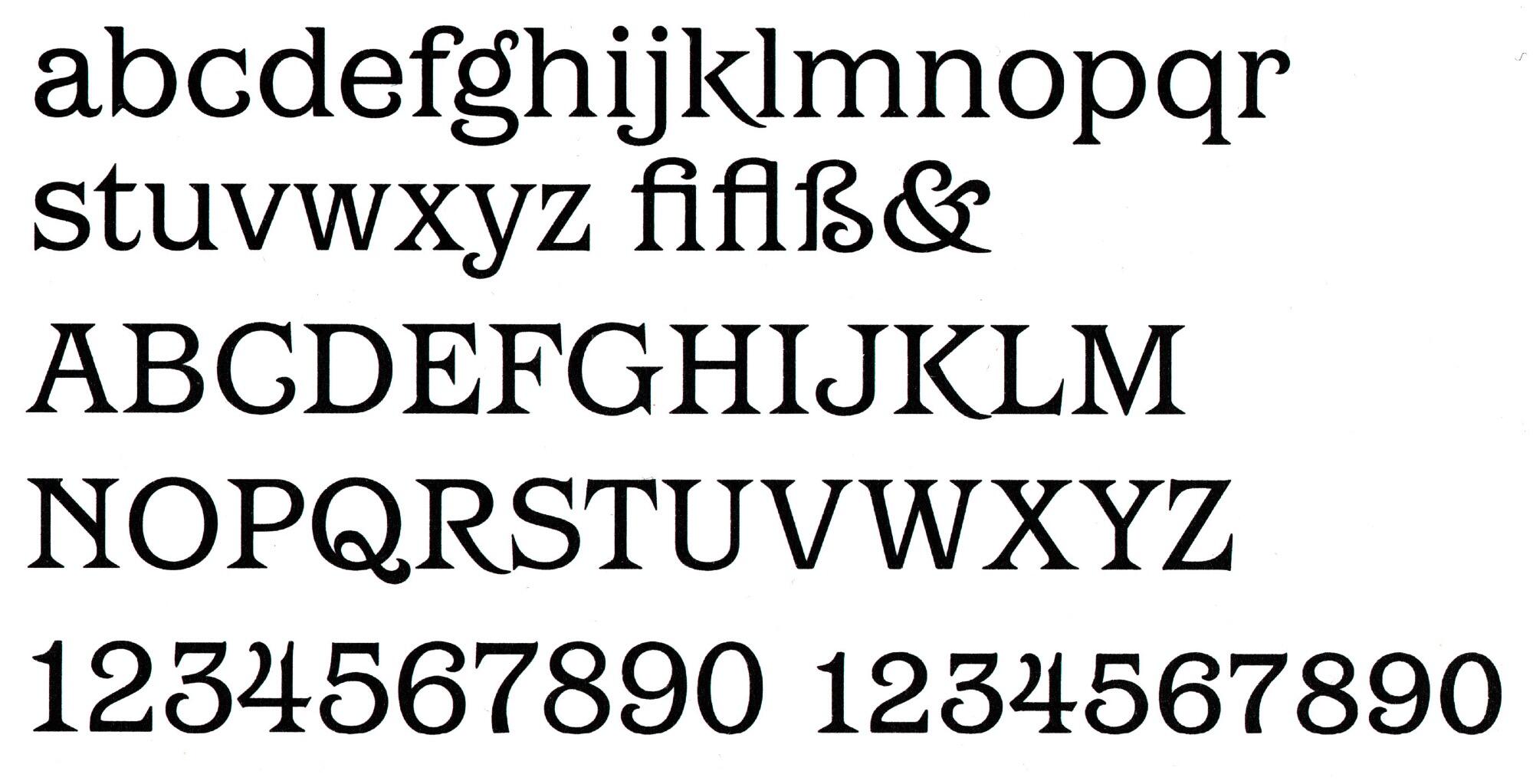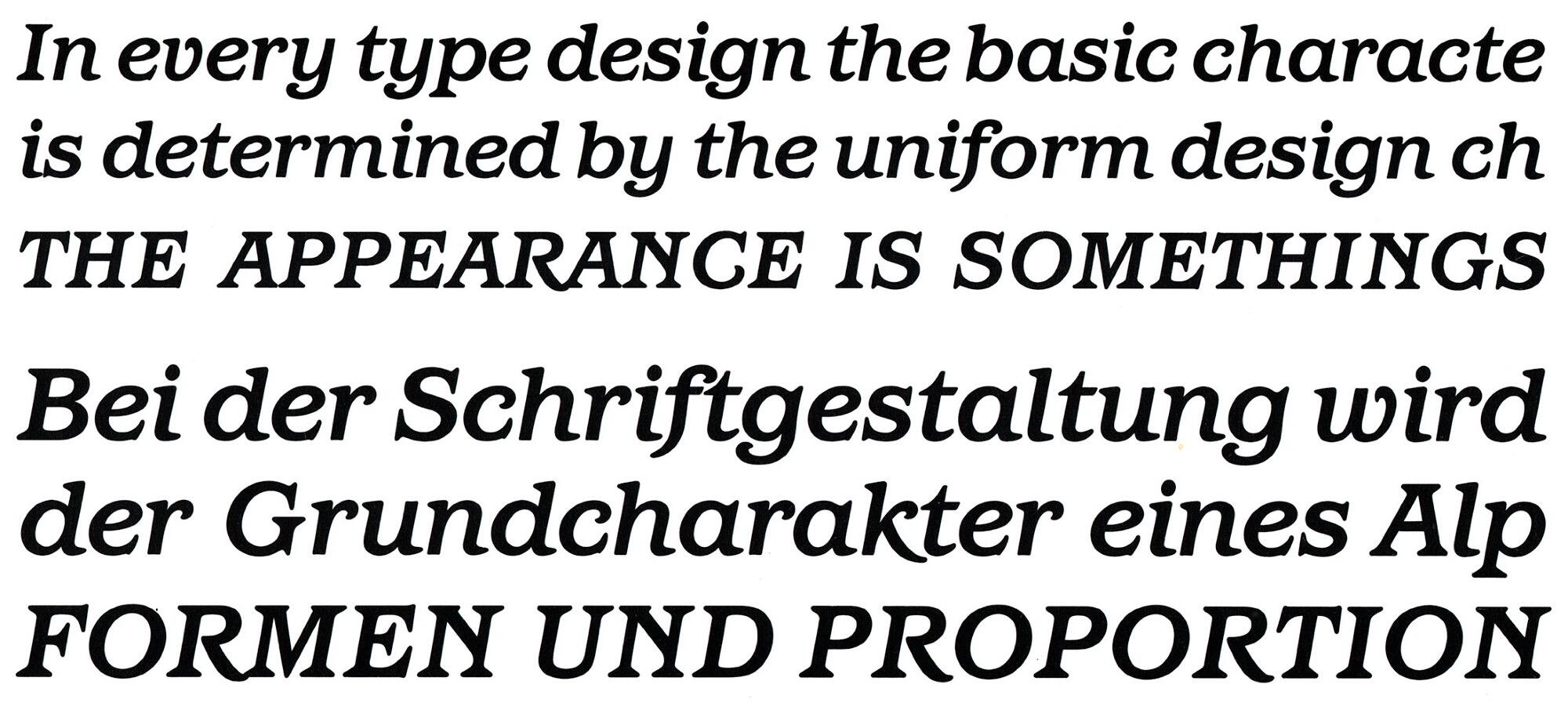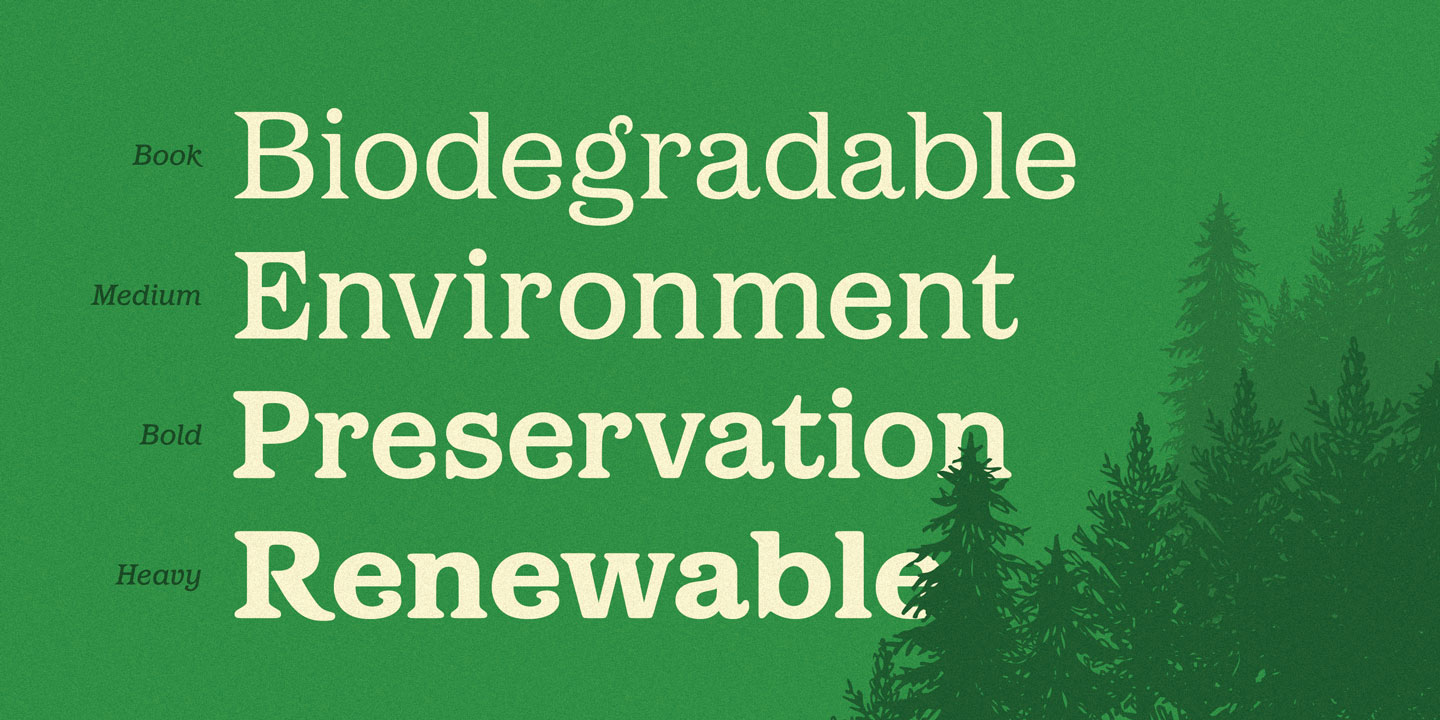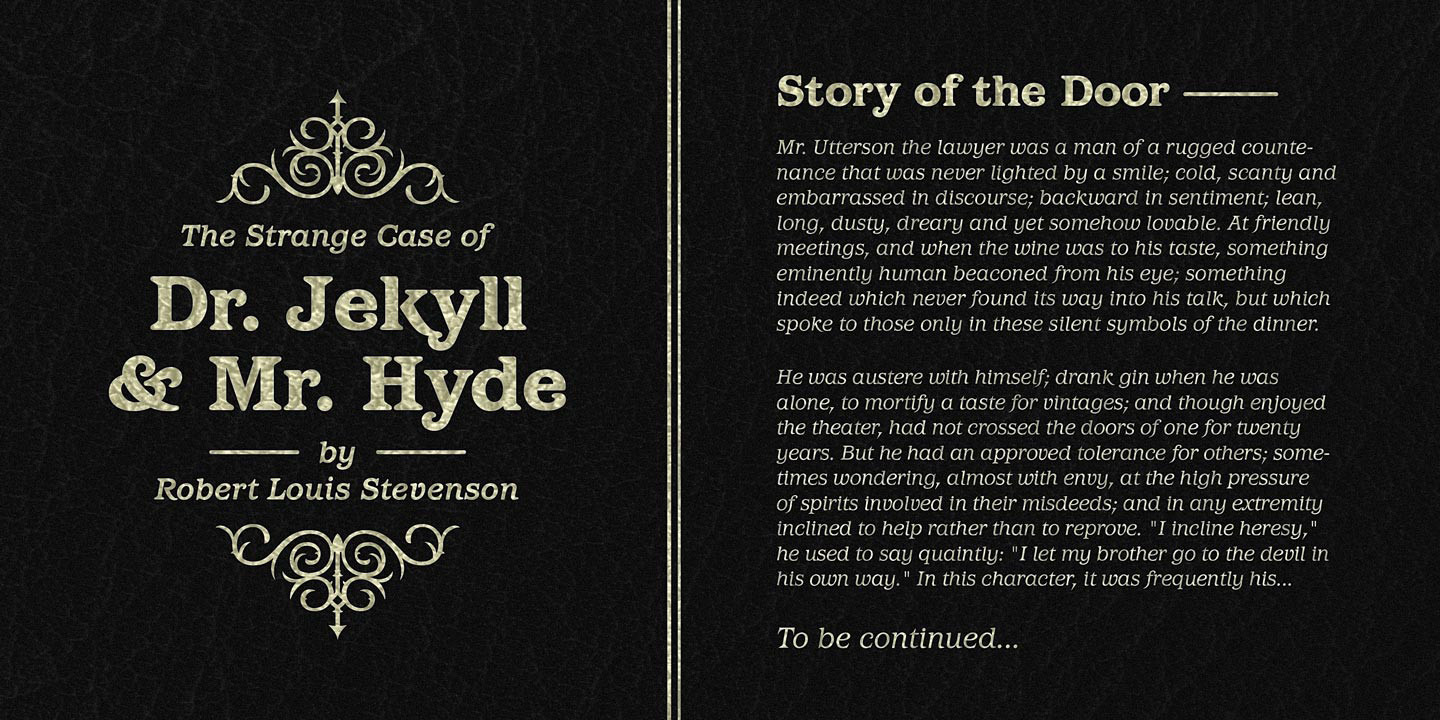
- 1981
- Antiqua humanistisch
Die ITC Barcelona von Ed Benguiat erschien 1981 als Fotosatzschrift über die International Typeface Corporation. Zur Familie gehören vier Strichstärken mit Kursiven, die heute auch digital verfügbar sind.